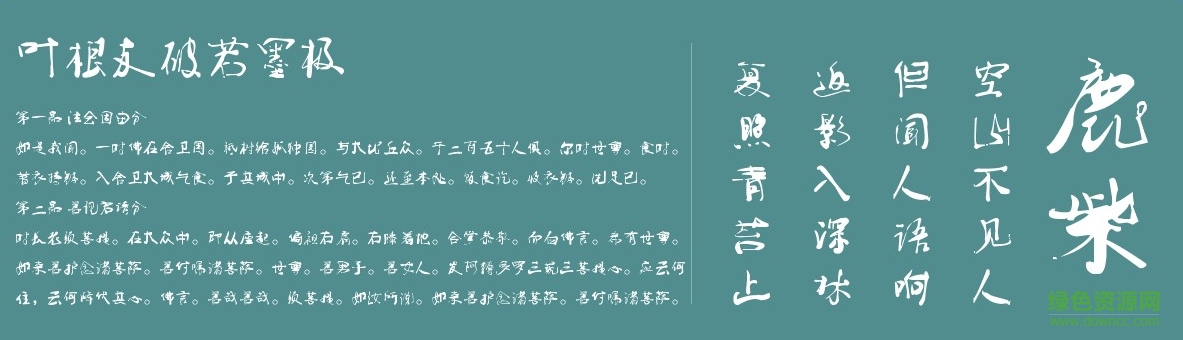
葉根友破若墨極是一款由知名書法家葉根友創(chuàng)造的字體,比劃圓潤,適用于廣告、藝術(shù)設(shè)計(jì),海報(bào)設(shè)計(jì)等方面,有需要的朋友們不要錯(cuò)過了。歡迎大家來綠色資源網(wǎng)踴躍下載哦!
葉根友破若墨極是一款特殊的字體,不是傳統(tǒng)的毛筆書寫,是用IPAD和手指寫成的,感謝高科技帶給我們的書法體驗(yàn),這樣的創(chuàng)作很美妙,相信以后還會(huì)出來更多這樣科技與書法結(jié)合的字體作品,這套葉根友破若墨極的字體的筆畫與傳統(tǒng)的毛筆創(chuàng)作的筆鋒是完全不一樣的,包含圓角,點(diǎn)、橫等都有令人意想不到的效果。
葉根友破若墨極,用途廣泛,是葉根友先生的手寫字體,適合場(chǎng)合很多,各位字體收藏者可以來看看。